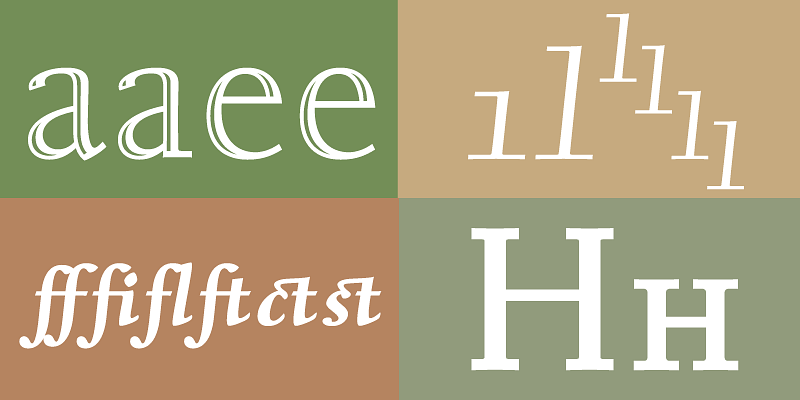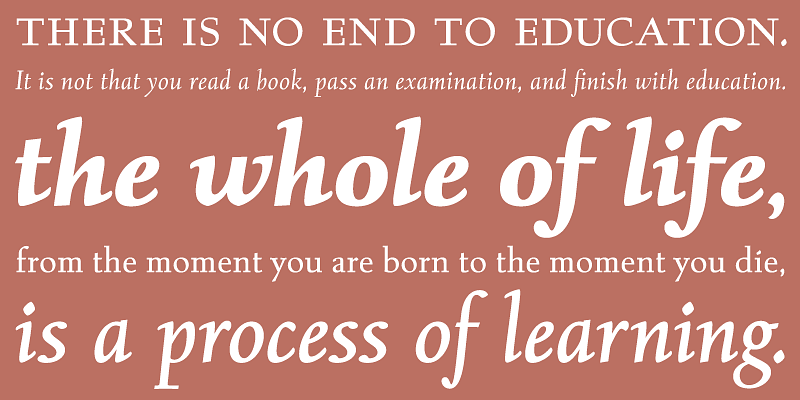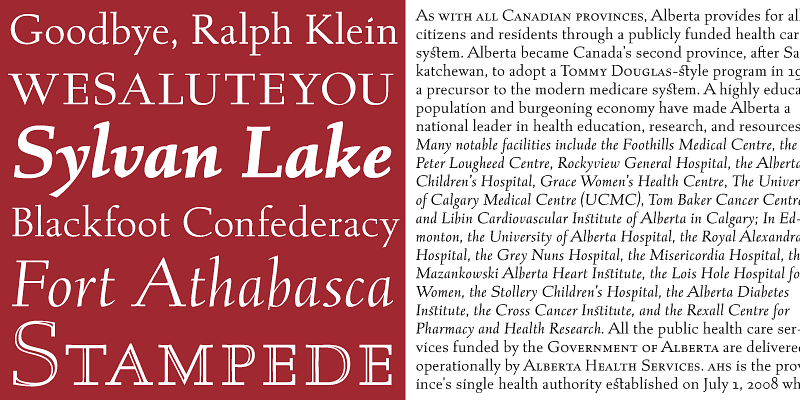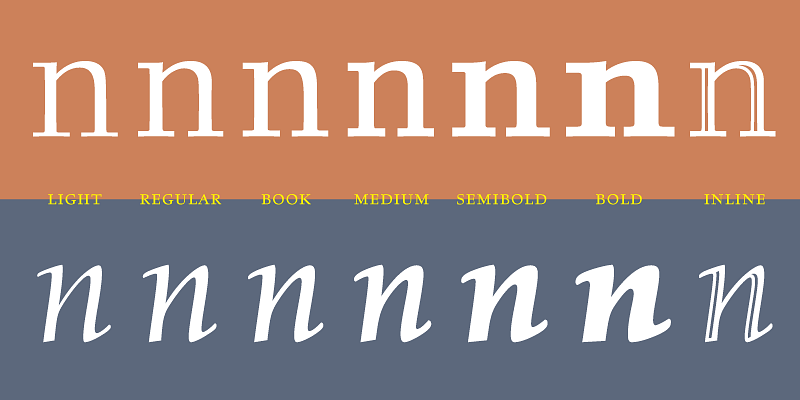
Albertan a été la première police de caractères Jim Rimmer à passer du type métallique au numérique. Lorsque la première police romaine a été coupée à 16 points en 1982, elle était destinée à la gravure à la main de livres à tirage limité chez Pie Tree Press, l’entreprise de Jim.